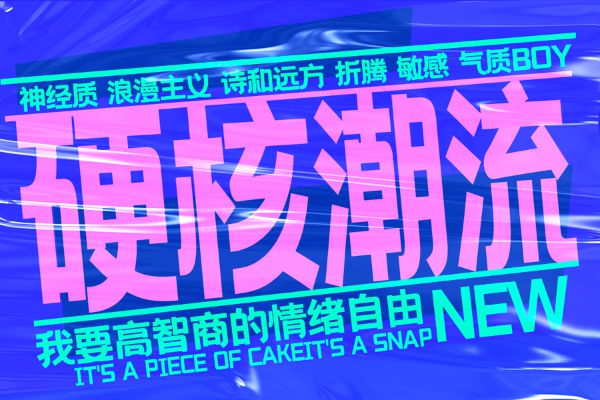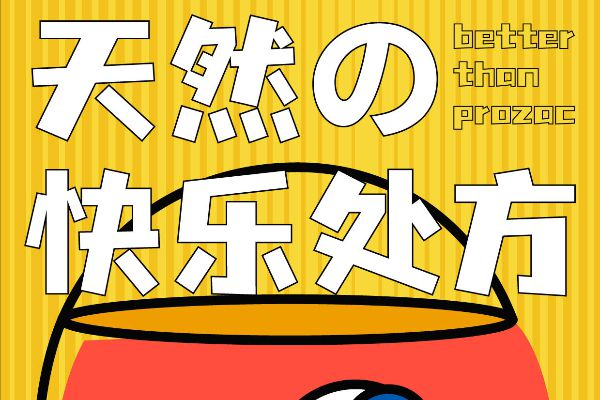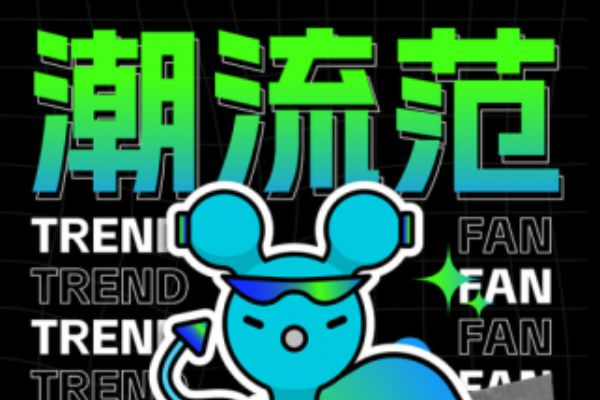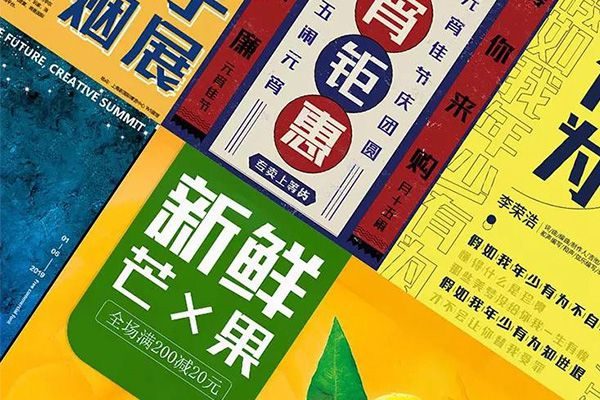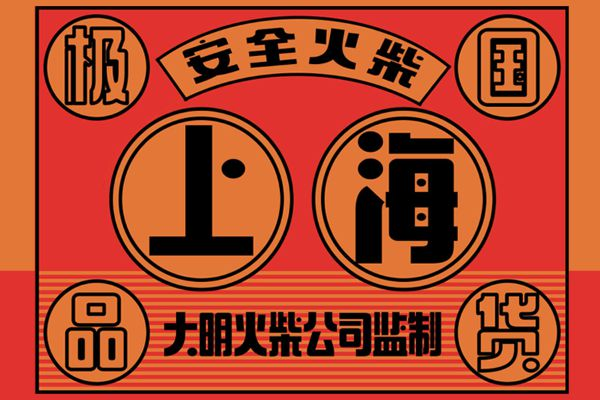
创意字体是免费字体吗?分享 10 个可以免费商用的创意字体
创意字体可以让你的设计作品、你的品牌信息,不再仅仅是冰冷的文字排列,能能够瞬间抓住观者的眼球,留下深刻的印象。尤其是在互联网的媒介,公众号的推文图片、抖音的视频字幕、网站的文字排版都非常适合使用一些创意字体,本文就给大家介绍一下创意字体是免费字体吗?以及分享 10 个可以免费商用的创意字体。
一、 什么样的字体是创意字体
创意字体不像“衬线体”或“无衬线体”那样有一个非常严格的分类定义。它更像是一个对于字体风格的一个区分,包含了那些为了表达特定情感、风格或为了吸引眼球而设计出来的、不拘泥于传统规则的字体。
创意字体可以说是非标准的字体,它们可能是造型独特、富有表现力、视觉冲击力强、打破常规的,与我们日常阅读的报纸、书籍中常见的标准字体(如宋体、黑体)不同,标准字体更注重清晰度、易读性和通用性,以满足大量文本的阅读需求。
所以,当你需要让你的品牌Logo脱颖而出,或者为海报、标题、包装增添独特的魅力时,创意字体无疑是你的最佳选择。
三、 10 款免费商用的创意字体
1. 字由文艺黑
字由文艺黑是一款由字由平台推出的,专为现代文艺场景和品质生活设计而生的无衬线(黑体)字体。它将“文艺”与“黑体”两种看似对立的风格巧妙融合,既保留了黑体字体的简洁、现代、易读性强的特点,又注入了人文的温度和艺术的雅致。
字由文艺黑摆脱了传统黑体的冰冷与呆板,以其清雅隽永的笔触和考究的字形结构,旨在为文字注入情感,传递出一种不喧哗、自有声的文艺情怀,如果想用一些更加灵动的黑体,字由文艺黑是很不错的选择。这也是字由平台使用量最多的免费创意字体。
1. 优设标题黑
优设标题黑是一款由优设联合字由平台推出的粗体黑体。“标题黑”直接点明了其核心用途,主要是在一些标题中使用,在复杂的信息流中,以最直接、最具冲击力的方式抓住受众的眼球。
优设标题黑以其粗壮的笔画、严谨的结构以及强大的视觉冲击力,如果您希望您的设计作品或品牌形象能够散发出强势、现代、权威、富有视觉冲击力的特点,那么“优设标题黑”是不错的选择。
1. 优设字由棒棒体
优设字由棒棒体同样是一款由优设联合字由平台推出的,充满活泼趣味和创意灵感的个性化字体。从字体的名字就能够体会到,这款字体突破了传统字体的规整与严肃,以其独有的圆润笔触、跳跃的字形和天真的风格,旨在为各种需要表达轻松、愉快、创意和年轻态度的设计场景注入无限活力与趣味。
1. 阿里妈妈数黑体
阿里妈妈数黑体是一款专为数字化时代商业传播和信息呈现而量身定制的黑体字体。阿里妈妈数黑体在设计上高度注重信息传达的清晰度、可读性和视觉统一性,力求在各种屏幕和印刷介质上都能展现出卓越的品质,在互联网、电商等场景都是不错的字体选择。
1. 联盟起艺卢帅正锐黑体
联盟起艺卢帅正锐黑体是一款极具锋利感和力量感的无衬线字体。联盟起艺卢帅正锐黑体打破了传统黑体的圆润或呆板,以其独特的几何结构和硬朗线条,在一些需要表达创新、速度、力量设计场景中,大家可以试试这款创意字体。
1. 字由芳华体
看名字大家应该就知道,这又是字由推出的一款字体,在创意字体方向上,字由创作了很多不错的字体,这款也不例外,字由芳华体将传统书法的灵动与现代设计的时尚感巧妙融合,笔画流畅舒展,字形优美雅致。
字由芳华体以其柔美灵动的笔画、雅致舒展的结构以及独特的浪漫气质,完美诠释了“芳华”二字的汉仪。如果您希望您的设计作品或品牌形象能够散发出优雅、浪漫、清新、富有艺术感染力的表达,可以尝试一下字由芳华体。
1. 演示佛系体
演示佛系体是一款充满禅意、随性与淡然的艺术字体。演示佛系体摆脱了传统字体的规整与束缚,以其独特的笔画结构和自然的形态,在一些需要表达宁静、自由、治愈和慢生活理念的设计场景中,非常适合这款字体。
1. 庞门正道标题体
庞门正道标题体是由知名设计师、设计教育者庞门正道团队推出的一款极具视觉冲击力和力量感的粗体黑体。和优设标题体类似,这款字体主要也是为了标题设计的,目的就是为了在众多信息中脱颖而出,以最醒目、最直接的方式抓住观者的注意力。
庞门正道标题体拥有磅礴大气的笔画、方正稳固的结构和强烈的现代感,在广告宣传、品牌推广、海报设计等标题中,使用会宣传效果起到非常好的作用。
1. 站酷快乐体
站酷快乐体是站酷联合设计师共同推出的一款充满童趣、活泼与趣味性的个性化字体。看到名字我都想到它的使用场景,“快乐”二字,直接点明了这款字体的设计初衷与核心风格——旨在通过文字传递积极向上、轻松愉悦的情绪。它突破了传统字体的严谨与拘束,以其圆润的笔触、跳跃的结构和不经意的俏皮感,旨在为各种需要表达轻松、愉快、创意和年轻态度的设计场景注入无限活力与感染力。
1. Aa厚底黑
Aa厚底黑是一款由Aa字库推出的,以其独特“厚底”特征而闻名的无衬线字体。Aa厚底黑融合了传统黑体的严谨与现代设计的简洁,以其粗壮的笔画、稳定的结构和深沉的力量感,旨在为各种需要表达稳重、力量、科技和工业美学的场景提供坚实的视觉支持。